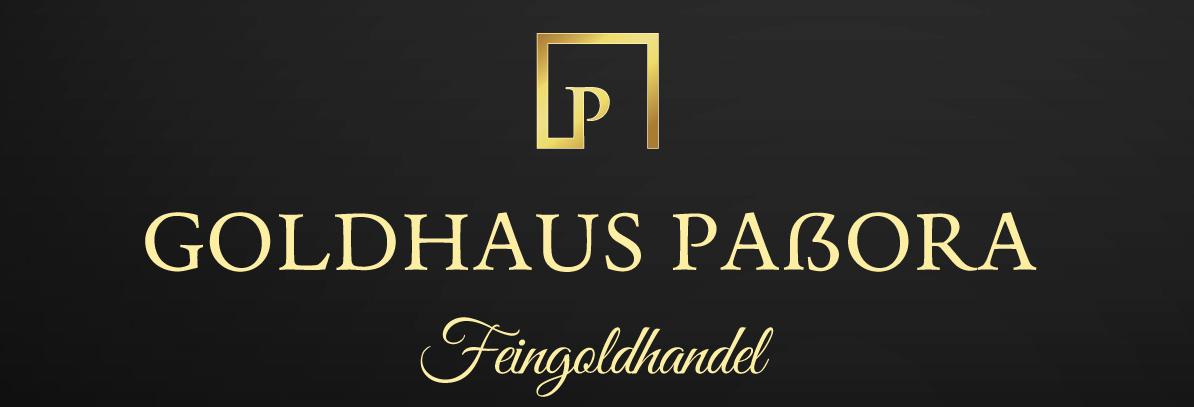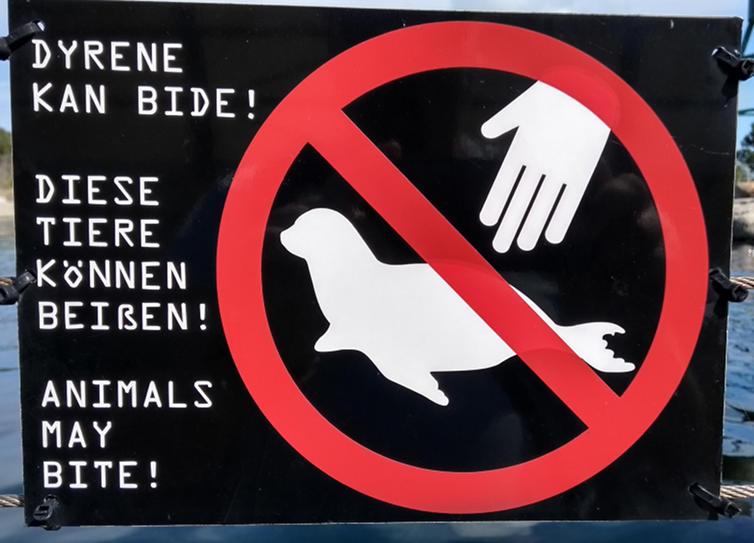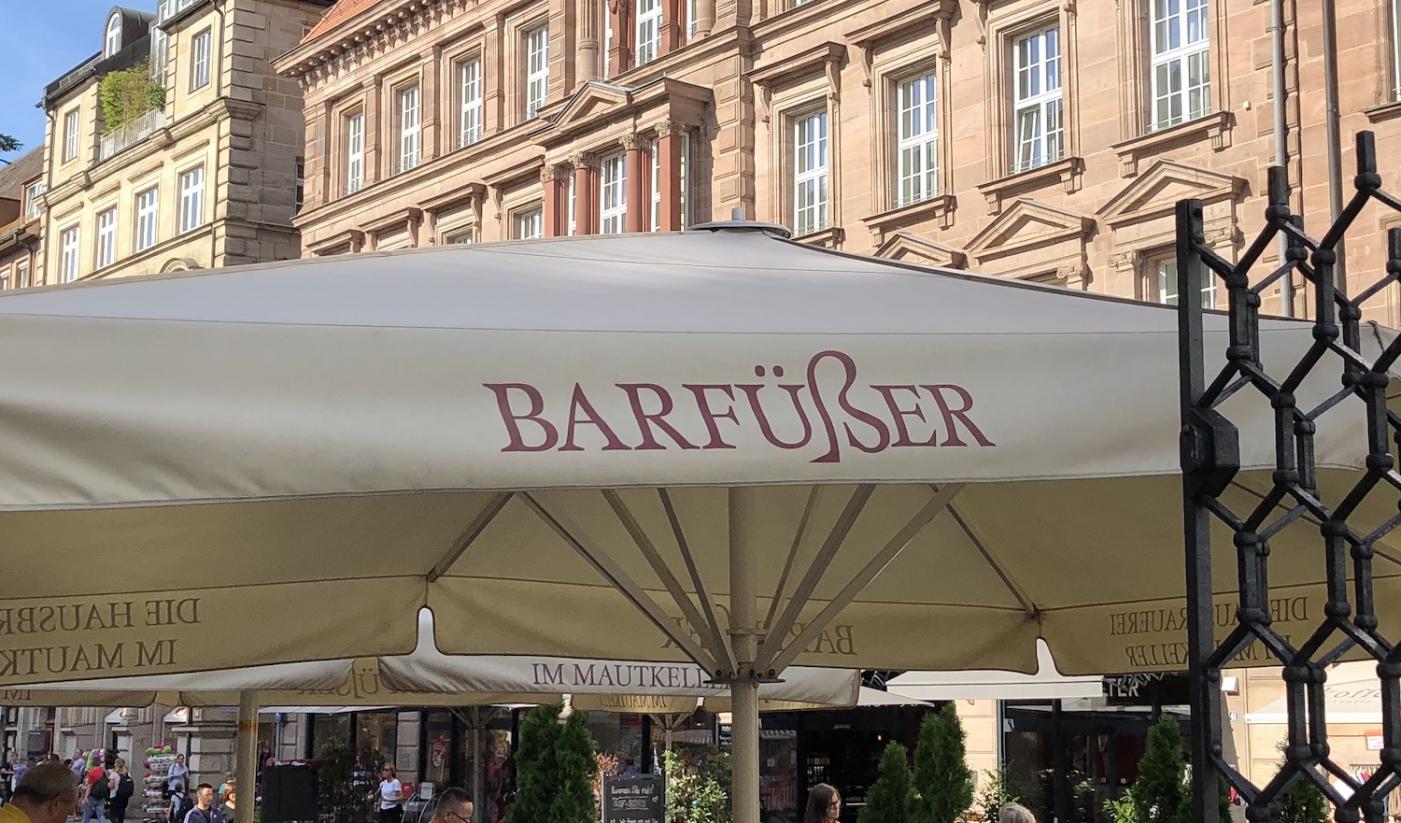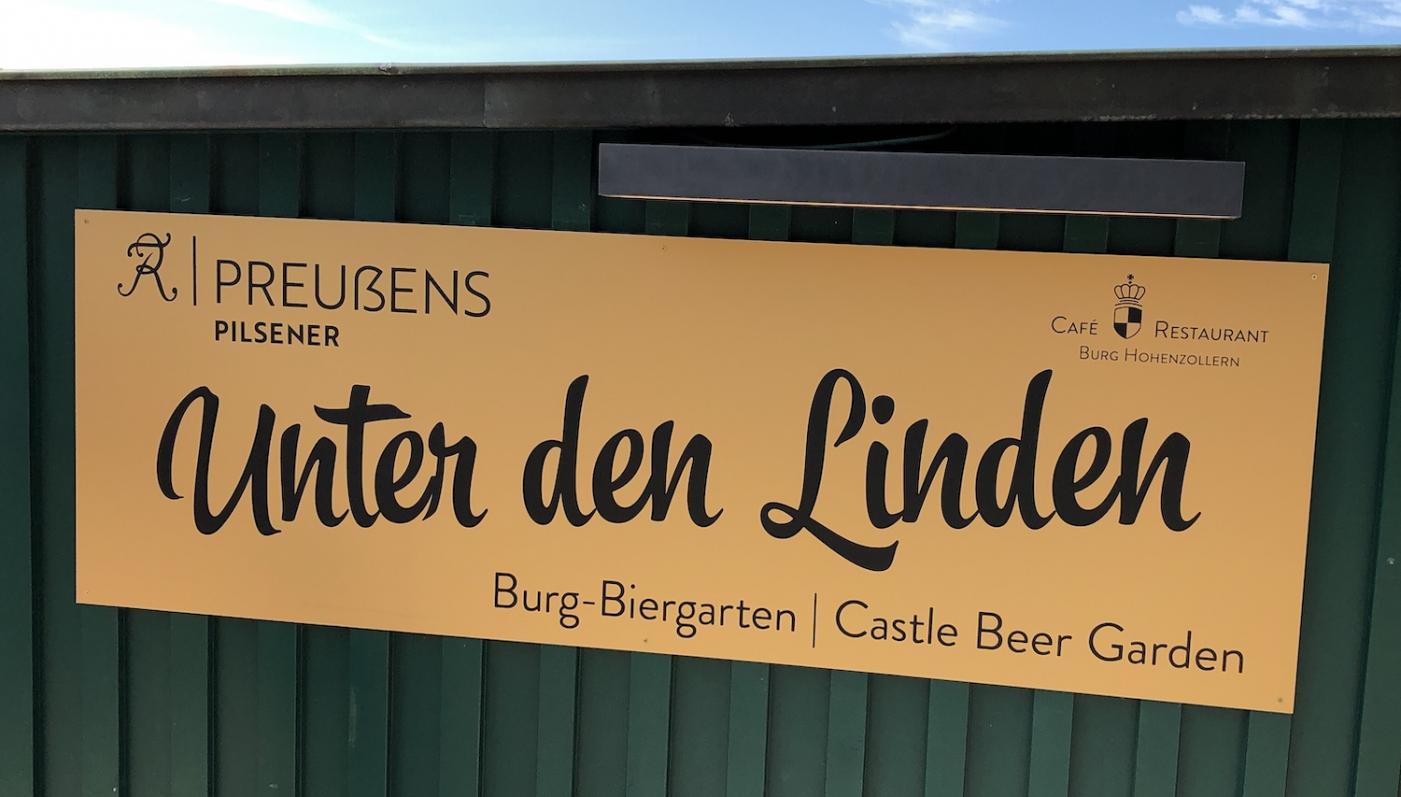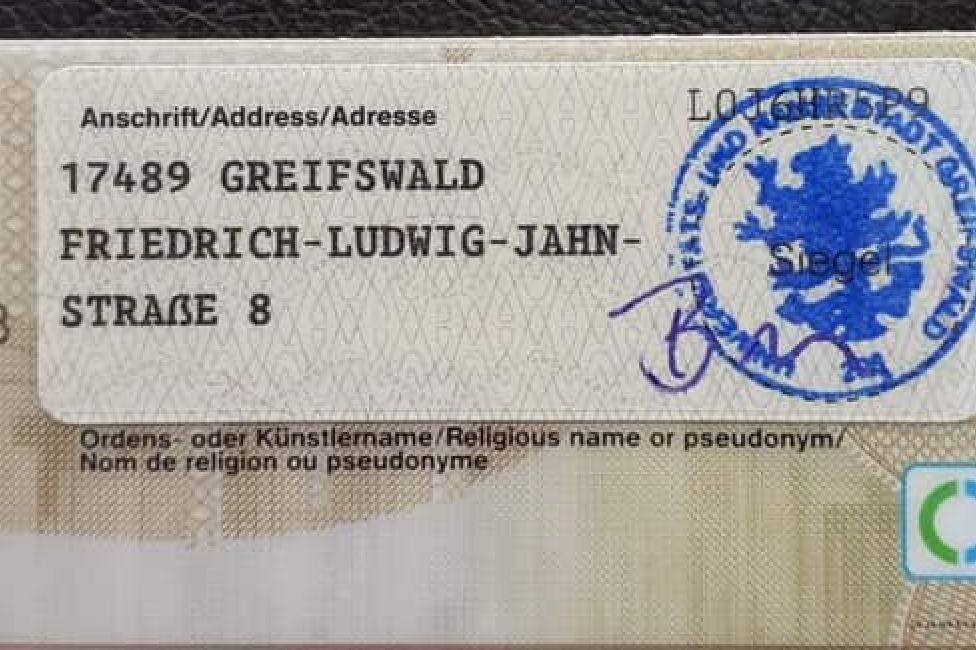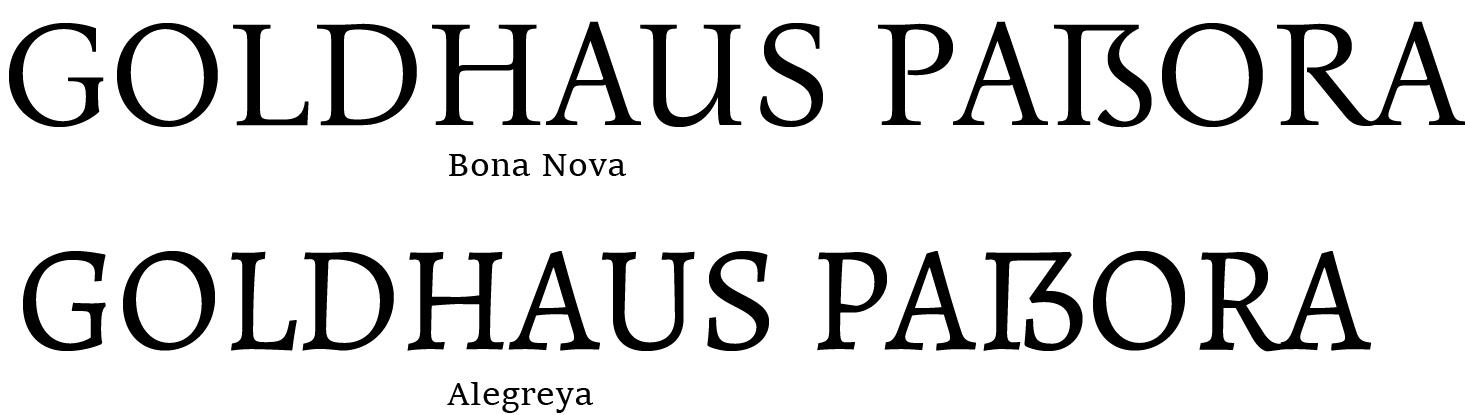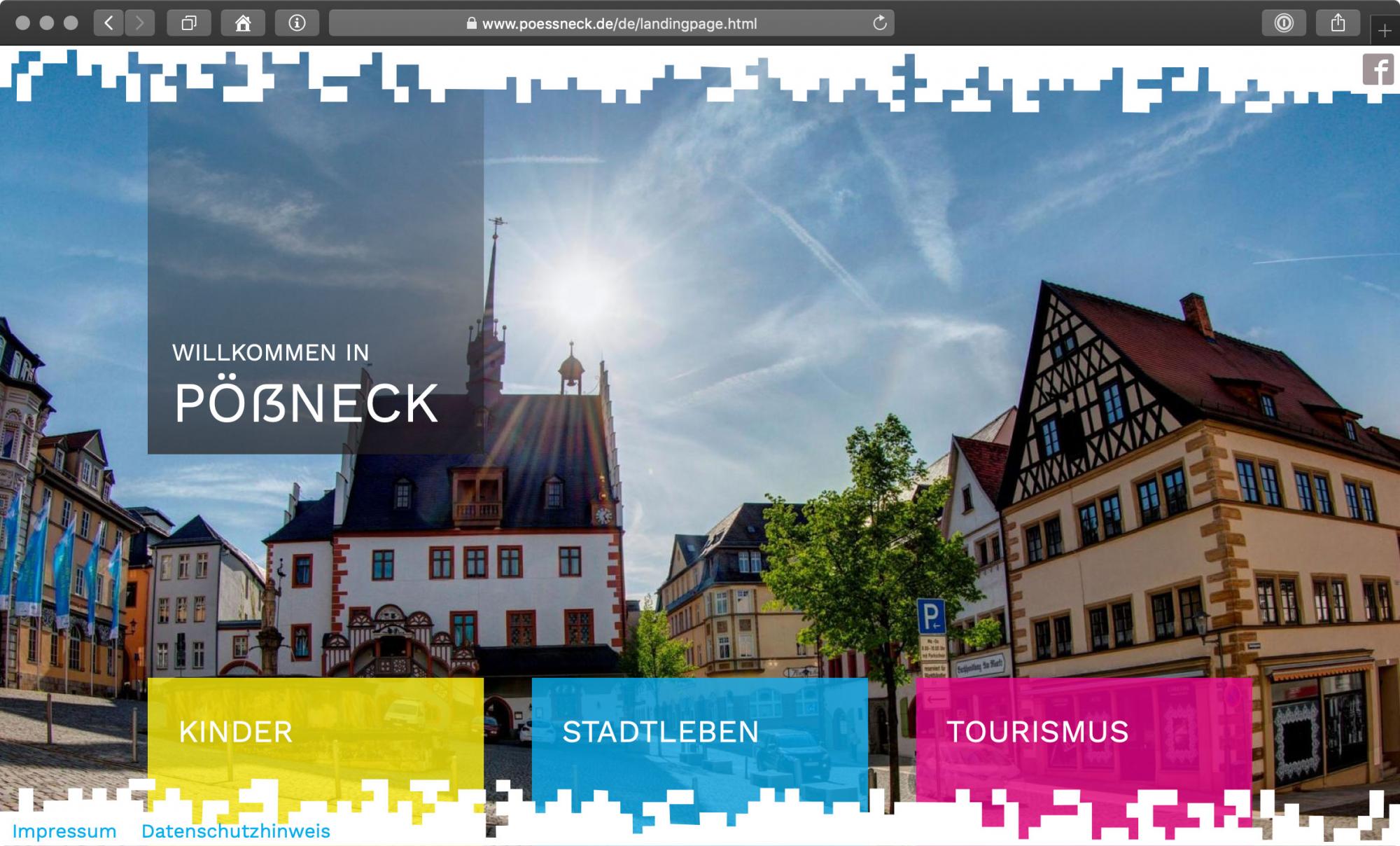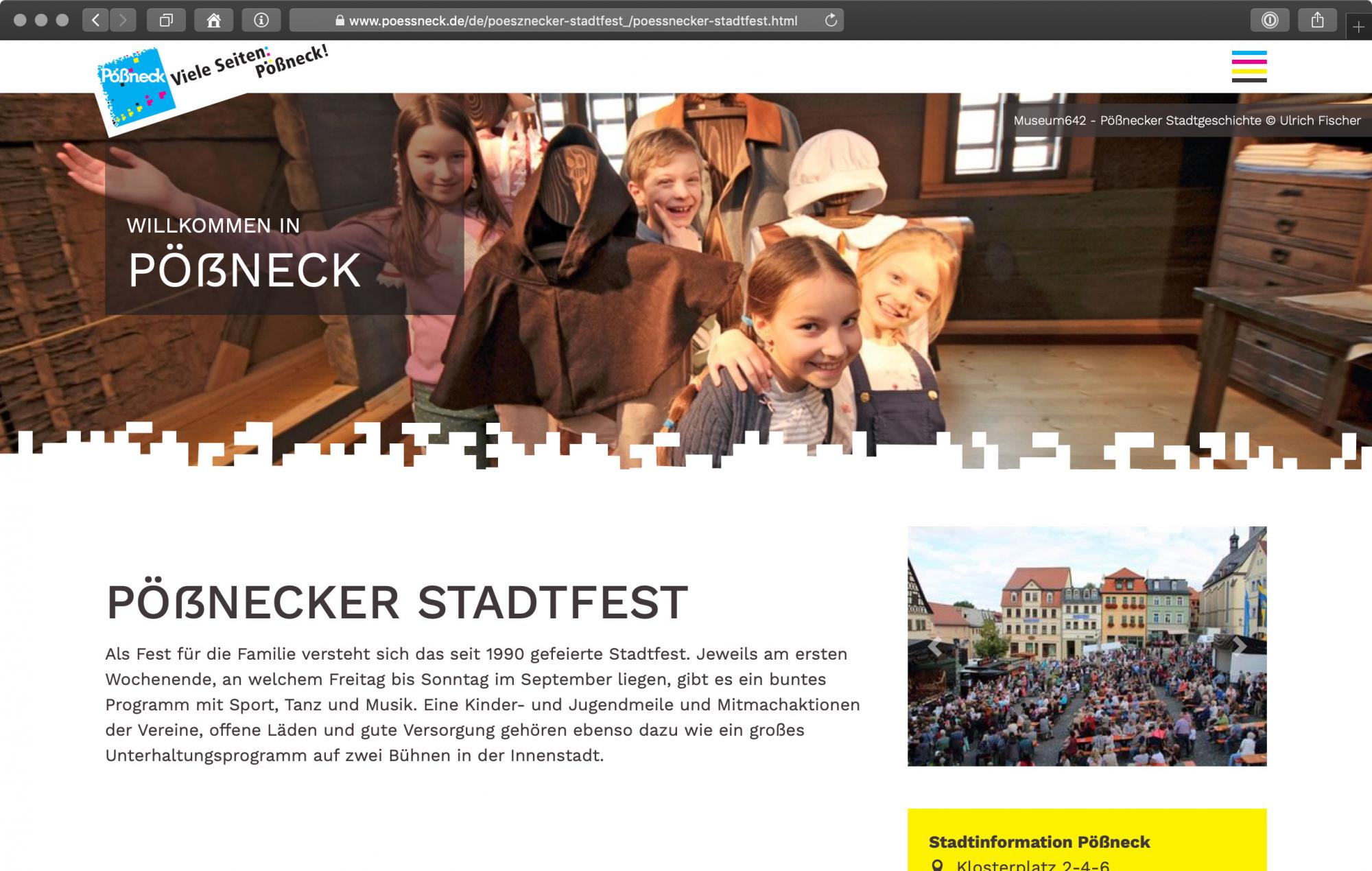
Wenn man kein großes  hat, nimmt man zum Ausgleich einfach ein besonders großes kleines …
Gefunden in Nürnberg, wobei die an anderer Stelle den Schriftzug auch mit normal großem kleinen ß  haben.
Und zum Ausgleich hier noch ein Fundstück von der Burg Hohenzollern:
Ich bin ja kein Fachmann, aber an dieser  Lösung könnte ich Gefallen finden.
Hier würde ich die Form SZ als störend empfinden. Und SS würde ich da schon
gar nicht sehen wollen. Mr. Austin
hier stolpere ich mehr über den anstrich vom r bei "Unter" als über das versal-ß
Stimmt … der ist mir vor lauter Fokus auf das Versal-S gar nicht aufgefallen.
Apropos Gründe, das ẞ in deine Fonts einzubauen
Grund 371: Damit das CD/CI nicht komplett umgeschmissen werden muss, weil plötzlich mal ein deutscher Text mit ß auftaucht
Animals may bite!
Erinnert mich an die " Astpreißische " Variante. - Ich glaube bei Lenz  gesehen:
"Es werd jeraten, dem Lewen nich zu zerjen!  Er mecht ouch beeißen !
Ich kann mich mit dieser Form des  Ess-Zett nicht anfreunden. Es wirkt immer ein wenig, wie ein Fremdkörper.
Mir geht es andersrum: Ich halte die links-oben-rechtwinklingen Versalesszetts zunächst stets für einen eingeschmuggelten, irgendwie griechisch-kyrillisch-georgischen Buchstaben. ;-)
Toll! Nun ist das ẞ wirklich angekommen. Gegen einen Deutſchen Perſonalausweis kann auch der traditionellste Traditionalist nix sagen.
Du könntest ja nach Hamburg in die STRAẞBURGER STRAẞE umziehen. Hättest dann sogar eine eigene U-Bahn-Station 🙂
SCHLUSS schreibt sich auch nicht mit scharfem ẞ. ;-)
Ich heiße ebenfalls Weiß. Lustig wird’s im Ausland, wenn der Name auf der Vorderseite der Personalausweises (Gemischtgeschrieben mit ß) mit dem Namen auf dem maschinenlesbaren Teil auf der Rückseite (Versalschreibweise mit SS) verglichen wird, das führt zuweilen zur einen oder anderen Diskussion. Die Österreicher sind da einen Schritt weiter, dort findet sich die Erklärung "ß enspricht ss" in mehreren Sprachen auf vielen Ausweisen.